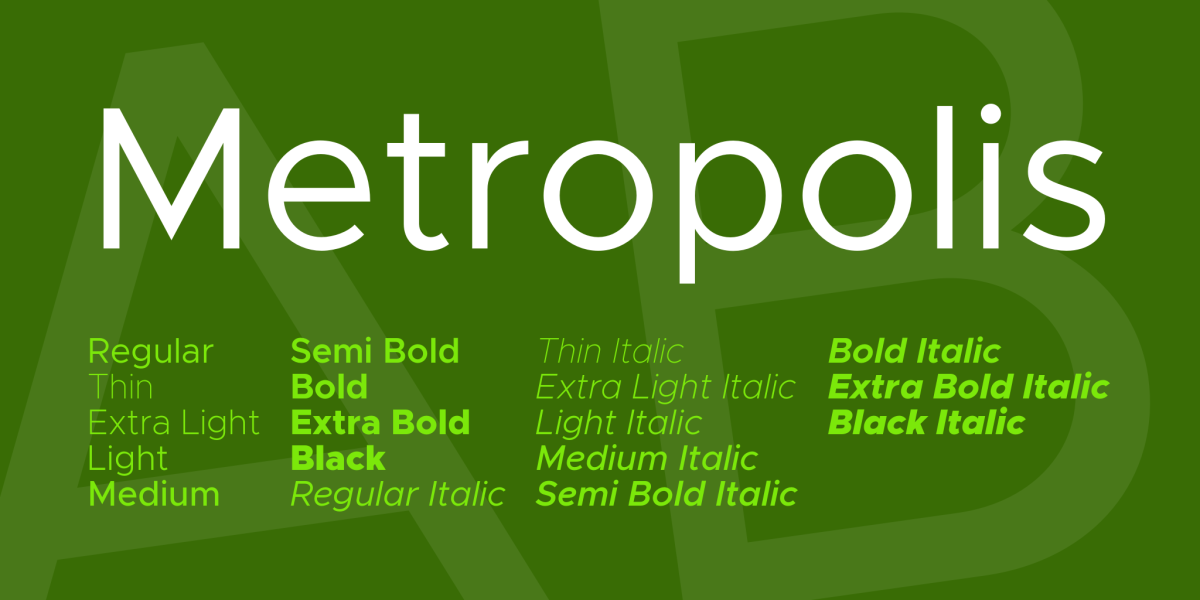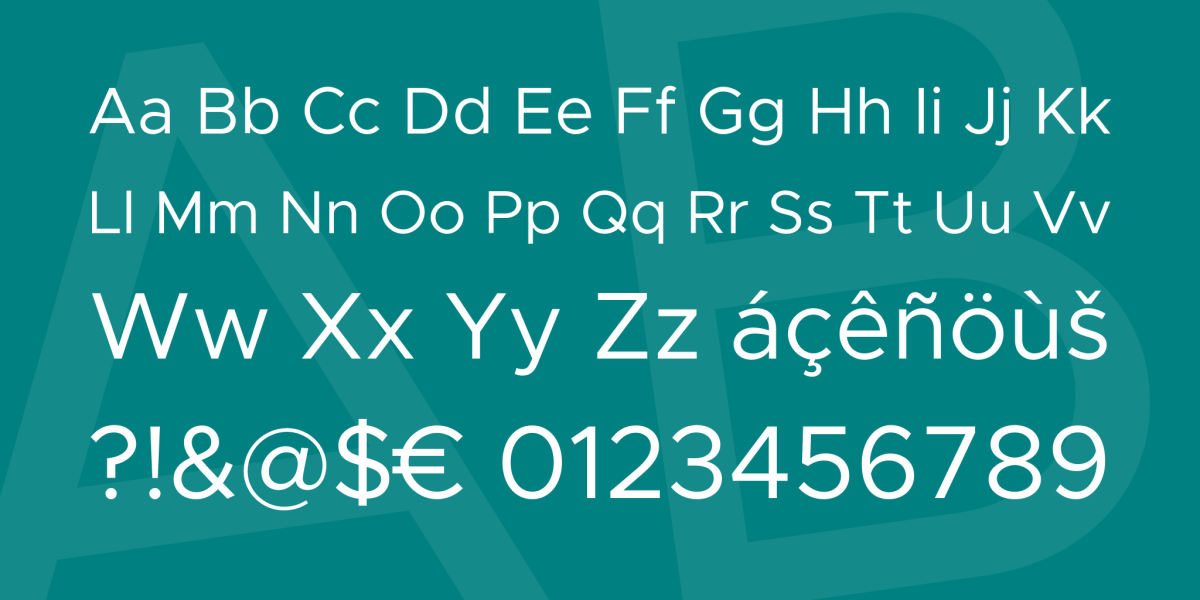
Metropolis Font là bộ phông chữ không chân (Geometric Sans-serif) hiện đại được thiết kế bởi Chris Simpson, lấy cảm hứng từ các kiệt tác Typography công nghiệp như Gotham và Proxima Nova. Với cấu trúc hình học chuẩn xác, tỷ lệ cân đối hoàn hảo và đường nét tối giản tinh tế, Metropolis là lựa chọn số một cho các thiết kế logo startup công nghệ, bộ nhận diện thương hiệu doanh nghiệp và bao bì sản phẩm cao cấp. Doozypack.vn cung cấp link Metropolis Font Download chuẩn kỹ thuật, giúp bạn sở hữu trọn bộ phông chữ thời thượng này mà không lo gặp bất kỳ lỗi hiển thị dấu tiếng Việt nào khi thiết kế in ấn.
Đặc điểm thẩm mỹ độc đáo của bộ font Metropolis
Metropolis không tìm kiếm sự phá cách ngẫu hứng; sức mạnh thị giác của nó đến từ sự chuẩn mực, tính kỷ luật của hình khối và khả năng truyền tải thông điệp một cách minh bạch nhất.
Cấu trúc Geometric Sans-serif chuẩn mực và hiện đại
Đặc trưng lớn nhất của Metropolis Font là các con chữ được xây dựng dựa trên những khối hình học cơ bản như hình tròn và đường thẳng dứt khoát. Thân chữ thẳng đứng kiêu hãnh, các nét vẽ có độ dày đồng đều tạo nên một nhịp điệu Typography vô cùng vững chãi, uy tín và chuyên nghiệp. Khi đặt Metropolis làm tiêu đề trên bao bì, thương hiệu của bạn sẽ ngay lập tức khẳng định được vị thế tiên phong, đáng tin cậy và bắt kịp xu hướng đồ họa tối giản quốc tế.
Độ mở chữ rộng và khả năng hiển thị vượt trội
Các ký tự của Metropolis Font Việt hóa sở hữu tỷ lệ x-height thoáng đãng cùng khoảng hở trong chữ (counter) rộng rãi. Nhờ đó, phông chữ này duy trì được độ sắc nét và khả năng đọc hiểu xuất sắc ở cả kích thước tiêu đề lớn trên nắp hộp giấy lẫn kích thước siêu nhỏ trên tem nhãn dán chai lọ, giúp người xem tiếp nhận thông tin bảng thành phần hay hướng dẫn sử dụng mà không hề bị mỏi mắt.
Ưu điểm nổi bật của bản Metropolis Font Việt hóa
Khi ứng dụng các phông chữ hình học quốc tế vào thị trường trong nước, sự chỉn chu về dấu câu là yếu tố quyết định đến tính chuyên nghiệp của bản thiết kế:
- Khắc phục triệt để lỗi dấu tiếng Việt: Phiên bản Việt hóa đã được đội ngũ thiết kế trau chuốt thủ công từng dấu câu. Các dấu sắc, huyền, hỏi, ngã, nặng được vẽ với tỷ lệ cân đối, đặt ở vị trí thoáng đãng so với thân chữ, không gây cảm giác chắp vá hay đè nét làm mất tính thẩm mỹ hình học.
- Hệ thống độ dày nét (Weights) đồ sộ: Từ bản Thin siêu mảnh đến bản Extra Bold mạnh mẽ, Metropolis đáp ứng đầy đủ yêu cầu phân cấp thông tin khoa học trên mọi ấn phẩm bao bì.
| Biến thể Font | Đặc điểm thị giác | Ứng dụng đề xuất tại Doozypack.vn |
| Metropolis Light | Thanh mảnh, tinh tế, hiện đại | Dùng cho ghi chú phụ, thông số kỹ thuật trên bao bì mỹ phẩm. |
| Metropolis Regular | Cân đối, thông thoáng, dễ đọc | Dùng cho nội dung hướng dẫn sử dụng, bảng thành phần (Body text). |
| Metropolis Bold / Black | Dày dặn, vững chãi, nổi bật | Dùng làm tiêu đề chính, tên sản phẩm hoặc logo thương hiệu. |
Lời khuyên từ xưởng in: Nếu bạn đang thiết kế bao bì sản phẩm công nghệ hoặc thời trang tối giản tại Doozypack.vn, hãy ưu tiên dùng Metropolis Bold Font Free Download cho tên thương hiệu. Sự vững chắc của khối chữ hình học sẽ tạo niềm tin rất lớn cho khách hàng ngay từ cái nhìn đầu tiên trên kệ trưng bày.
03 Ứng dụng thực tế của font Metropolis trong sản xuất bao bì tại Doozypack.vn
Sự hiện đại và tinh tế của Metropolis mang lại hiệu ứng thị giác đắt giá trên các dòng sản phẩm bao bì thực tế do Doozypack.vn sản xuất:
- Hộp đựng sản phẩm Công nghệ & Phụ kiện thông minh: Nét chữ hình học của Metropolis rất tương đồng với thiết kế của các thiết bị điện tử, tạo nên sự đồng bộ chuyên nghiệp từ sản phẩm đến vỏ hộp.
- Bao bì Mỹ phẩm tối giản & Dược mỹ phẩm: Tiêu đề thương hiệu in bằng font Metropolis trên giấy Ivory cán màng mờ tạo cảm giác an toàn, minh bạch và cao cấp.
- Túi giấy doanh nghiệp & Cửa hàng thời trang: Tên thương hiệu in bằng font Metropolis Bold màu đen tối giản trên nền túi giấy trắng giúp khẳng định phong cách hiện đại và đẳng cấp.
Lưu ý kỹ thuật khi in ấn với phông chữ hình học Metropolis
Việc sản xuất bao bì thực tế sử dụng các phông chữ hình học đòi hỏi sự am hiểu kỹ thuật chuyên sâu tại xưởng in Doozypack.vn: